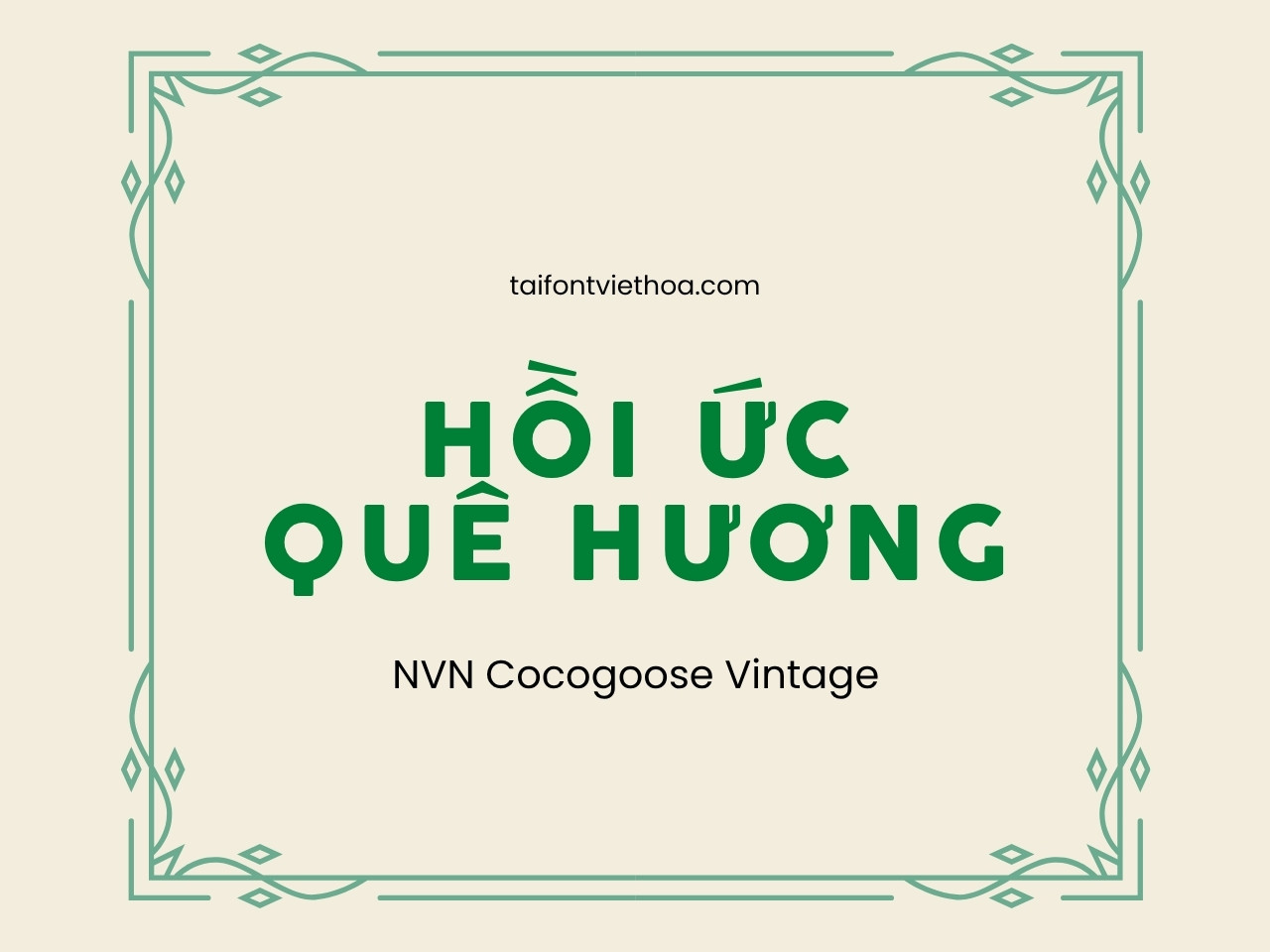
Giới thiệu về font Cocogoose Vintage
Cocogoose Vintage là một biến thể đặc biệt thuộc bộ font Cocogoose, được phát triển bởi Zetafonts – một studio thiết kế font nổi tiếng đến từ Ý. Font mang phong cách retro mạnh mẽ, lấy cảm hứng từ thiết kế công nghiệp và hình học cổ điển những năm 1920–1930. Bản Việt hóa mang tên NVN Cocogoose Vintage được thực hiện bởi NVN Font, hỗ trợ đầy đủ tiếng Việt với hệ thống dấu rõ ràng, sắc nét và được tối ưu cho các nền tảng thiết kế số. Ngoài tiếng Việt, font còn hỗ trợ hơn 60 ngôn ngữ khác thông qua bảng mã Latin Extended, mang lại sự linh hoạt cho các dự án toàn cầu. Font này đã được taifontviethoa.com chọn lọc, sưu tầm và ứng dụng thực tế trong nhiều dự án nhận diện thương hiệu, in ấn và truyền thông số tại Việt Nam.
Đặc điểm thiết kế và ứng dụng của Cocogoose Vintage
Cocogoose Vintage có thiết kế dày dặn, các đường nét vuông vức, đậm chất công nghiệp và hoài cổ. Với các đường viền hơi bo tròn, font tạo ra sự cân bằng giữa nét mạnh mẽ và thân thiện. Bộ font đi kèm nhiều style và chữ in hoa nổi bật, phù hợp để làm tiêu đề, logo, poster, biển hiệu và ấn phẩm quảng cáo lớn. Phần chữ cách đều, chắc chắn giúp tăng độ dễ đọc và tạo ấn tượng thị giác mạnh mẽ.
Font Cocogoose Vintage đặc biệt phù hợp trong thiết kế bao bì, biển hiệu cửa hàng, branding ngành thực phẩm, quán cà phê, cửa hàng thời trang, cũng như các chiến dịch marketing mang phong cách cổ điển hoặc công nghiệp. Các ngành nghề như quảng cáo, thiết kế đồ họa, nội thất, F&B và sự kiện đều có thể tận dụng hiệu quả của font này.